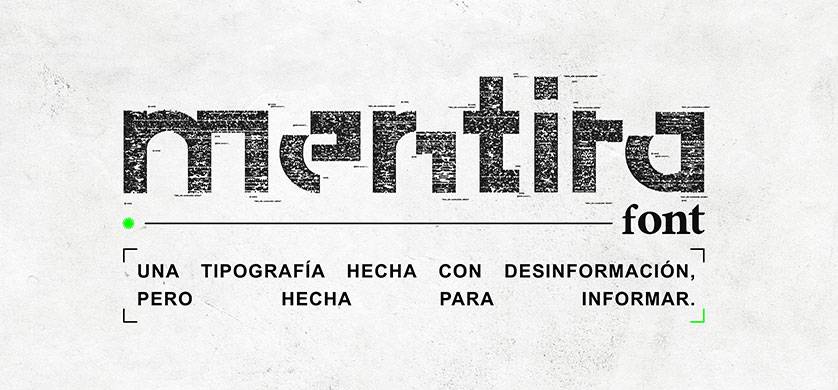
“Mentira Font”, la tipografía de Reverso y BBDO creada para exponer contenidos falsos
Esta campaña de concientización fue pensada para poner un freno a la desinformación en la Argentina durante el último proceso electoral, pero quedará como una herramienta fundamental al momento de exponer los datos erróneos. Mirá el video en la nota.
Es sabido que durante las elecciones los contenidos dudosos que circulan crecen de manera exponencial, lo que dificulta a las personas poder discriminar entre una noticia verdadera y una falsa, y finalmente perjudica a la democracia a la hora de votar con conciencia. Según fuentes de Chequeado.com, un contenido falso circula un 70% más que uno verdadero.
Es por esto que BBDO diseñó Mentira Font, esta fuente tiene un aspecto de letras rotas o decodificadas, a modo de generar una percepción de texto corrompido y de este modo, se convierte en una herramienta sencilla que permite cambiar la tipografía de una información falsa y de este modo evitar la viralización de datos engañosos durante los procesos electorales.
"Crear una tipografía es una manera simple de poner en agenda un tema muy complicado de explicar. Nos permite crear mensajes directos, porque la tipografía es lo que agrega el impacto", resumieron Gonzalo Palma y Agustín Fernández Madero, Group Creative Directors de BBDO Argentina.
La tipografía está a disposición para que los medios también puedan hacer uso de la misma en el sitio web de Reverso. La campaña cuenta además con contenido en redes sociales, gráfica y activaciones en medios.